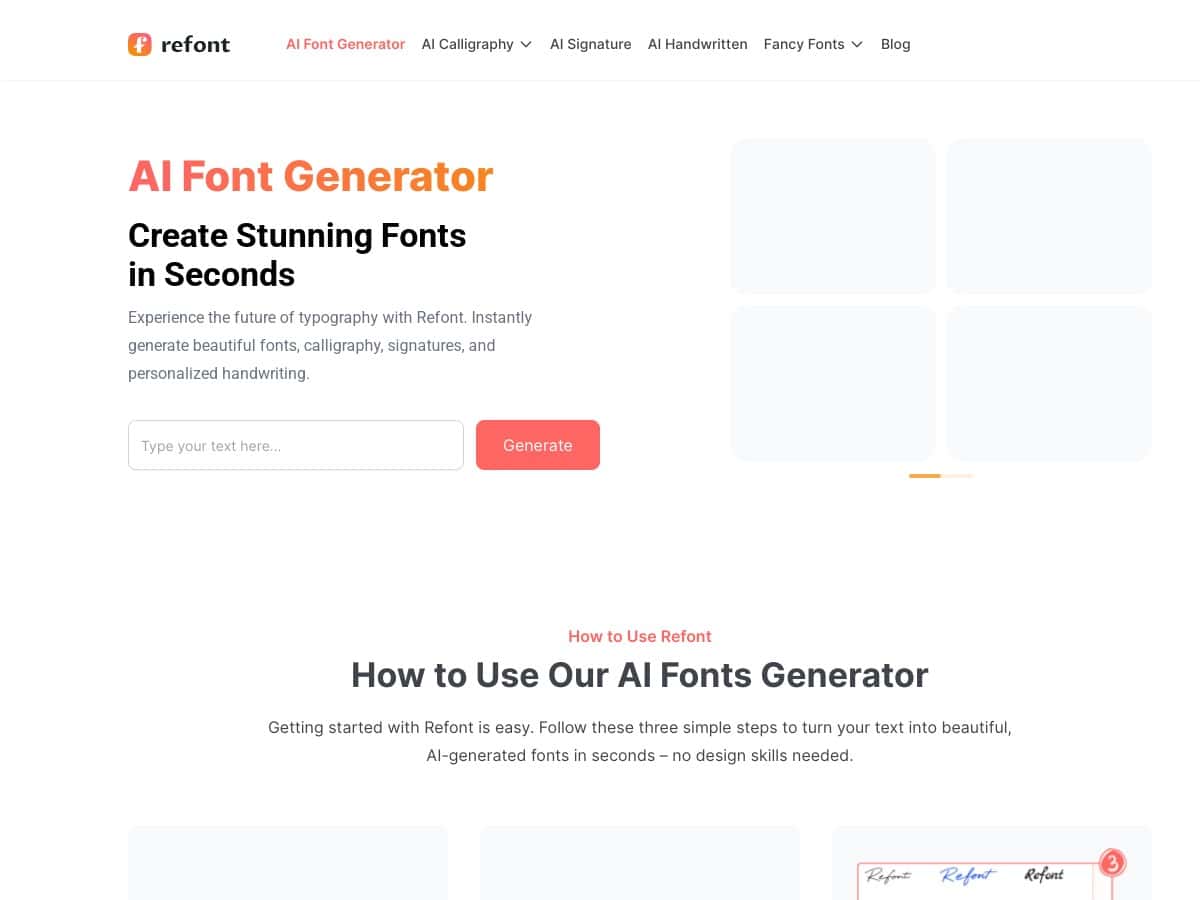
Refont.ai Bewertung – Der einfache Weg, stilvolle Schriftarten zu erstellen
Suchen Sie nach einer persönlichen Note für Ihre Social-Media-Beiträge oder Ihr Branding? Refont.ai verspricht eine einfache Möglichkeit, schöne Schriftarten und Texteffekte ohne Designkenntnisse zu generieren. Ich habe beschlossen, zu erkunden, ob dieses kostenlose Tool sein Versprechen hält. Wenn Sie neugierig sind, wie Sie mühelos Kalligraphie, Unterschriften oder ausgefallene Texte erstellen können, lesen Sie weiter für eine ehrliche Bewertung. Ich habe seine Funktionen getestet, um zu sehen, wie benutzerfreundlich und effektiv es wirklich ist.
Refont.ai Bewertung
Als jemand, der gerne mit Typografie experimentiert, aber kein professioneller Designer ist, fand ich Refont.ai überraschend unkompliziert. Die Benutzeroberfläche ist sauber und einfach, mit sofortigen Vorschauen Ihres gestalteten Textes. Ich liebte, wie schnell ich einfachen Text in elegante Kalligraphie oder stilvolle Social-Media-Schriftarten verwandeln konnte. Die Ausgaben erfolgen hauptsächlich als Bilder mit transparenten Hintergründen, perfekt für schnelles Teilen oder Branding-Visuals. Auch wenn Sie keine vollständigen Schriftdateien wie .ttf oder .otf herunterladen können, macht die Möglichkeit, sofort hochwertigen gestalteten Text zu generieren, es äußerst praktisch für die digitale Nutzung. Ich schätzte, dass keine Registrierung erforderlich war, was den Prozess völlig unkompliziert machte.
Hauptmerkmale
1. AI-Kalligraphie-Generator erstellt elegante handgeschriebene Stile aus Ihrem Text
2. AI-Unterschriften-Generator hilft bei der Erstellung personalisierter digitaler Unterschriften
3. AI-handgeschriebene Schriftarten-Generator produziert realistische, natürlich aussehende Handschrift
4. Ausgefallener Schriftarten-Generator verleiht Social-Media-Bios und -Beschreibungen Flair
5. Kalligraphie-Logo-Generator ermöglicht Logo-Designs mit Kalligraphie-Elementen
6. Hochauflösende herunterladbare Bilder mit transparenten Hintergründen
Vor- und Nachteile
Vorteile
• Sehr benutzerfreundlich mit einer einfachen Benutzeroberfläche
• Generiert sofort stilvolle Textbilder
• Ideal für Social Media, Branding und schnelle visuelle Inhalte
• Unterstützt mehrere Sprachen, einschließlich Chinesisch
Nachteile
• Begrenzte Optionen für tiefere Anpassungen oder Bearbeitungen
Zusammenfassung
Zusammenfassend lässt sich sagen, dass Refont.ai ein ausgezeichnetes kostenloses Tool ist, um auffällige Texteffekte ohne Aufwand zu erstellen. Auch wenn es keine installierbaren Schriftarten bietet, machen die Benutzerfreundlichkeit und die sofortigen Ergebnisse es zur perfekten Wahl für Social-Media-Beiträge, Branding-Visuals und schnelle Designprojekte. Wenn Sie in Sekundenschnelle schön gestalteten Text benötigen, ist Refont.ai auf jeden Fall einen Versuch wert.